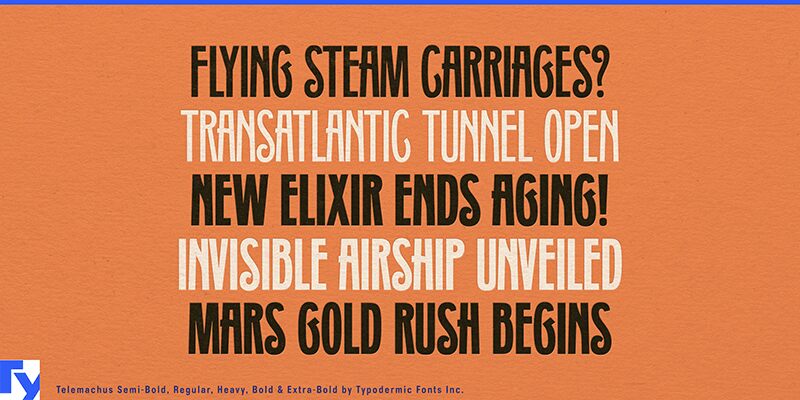
Telemachus SemiBold
Telemachus est une police sans empattement ultra-condensée, inspirée des caractères en métal du XIXe siècle et retravaillée pour le design contemporain. Sa hauteur d'x imposante et ses proportions étroites garantissent un impact visuel fort dans un espace horizontal restreint, tandis que ses terminaisons arrondies adoucissent sa tension verticale.
Idéale pour les titres, affiches, packagings et autres mises en page où l'espace est compté, Telemachus marie le caractère vintage à une forme moderne et épurée. Grâce à sa prise en charge étendue des langues latines, elle offre une voix assurée et distinctive pour la typographie d'affichage.